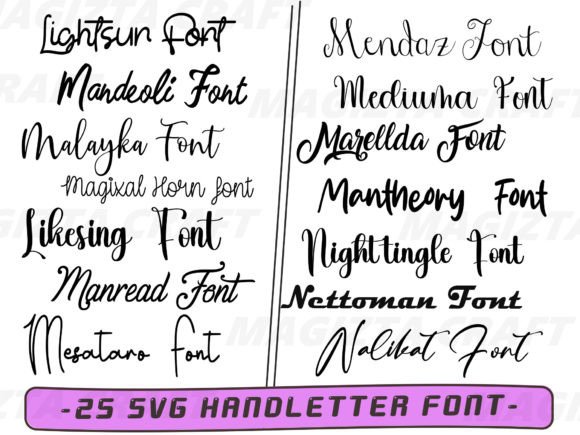
Handwritten Letter Font
Si vous recherchez des ressources de haute qualité comme Handwritten Letter Font, ce pack premium est un choix fantastique pour vos projets créatifs.
Conçu avec précision, Handwritten Letter Font offre des vecteurs nets, une typographie fluide et une licence commerciale pour une tranquillité d'esprit.
Que vous créiez des produits POD (impression à la demande), des invitations de mariage ou des visuels pour les réseaux sociaux, Handwritten Letter Font est un choix idéal.